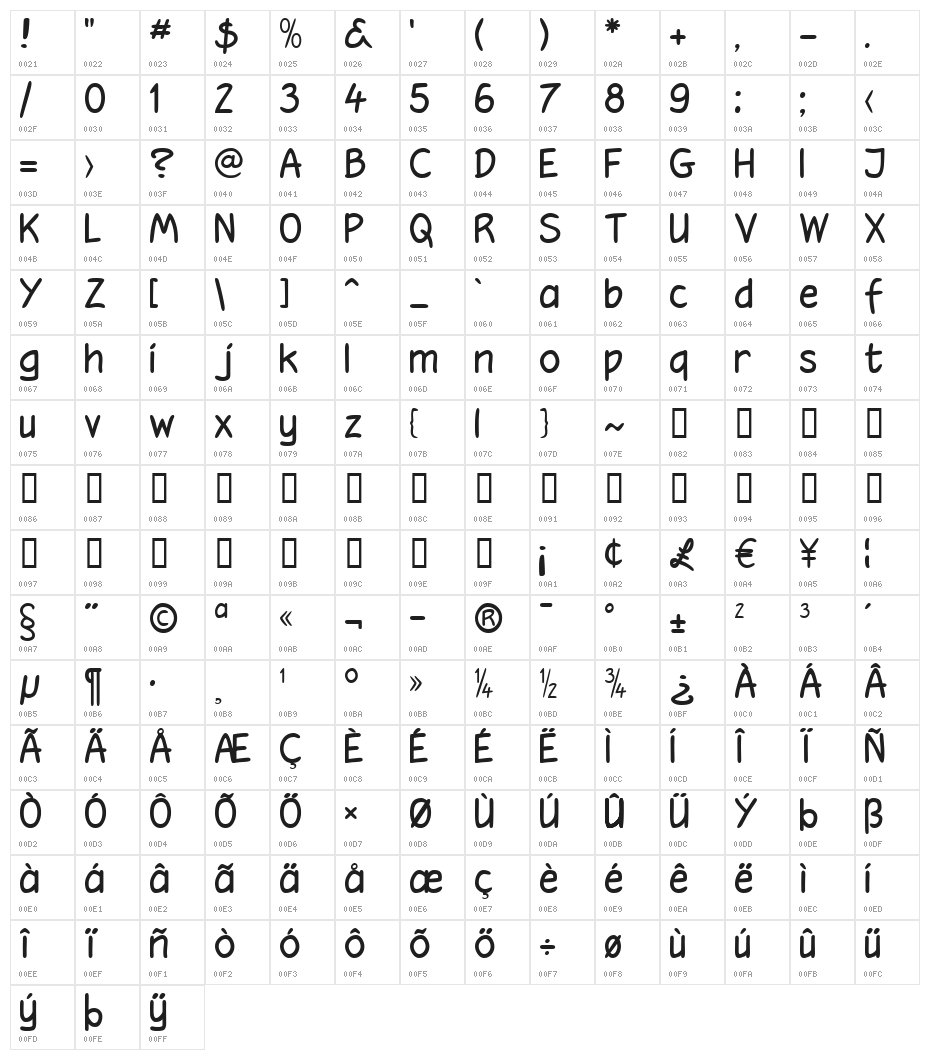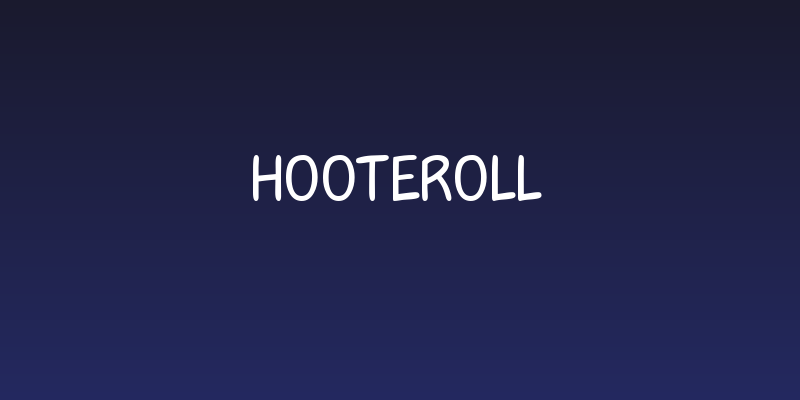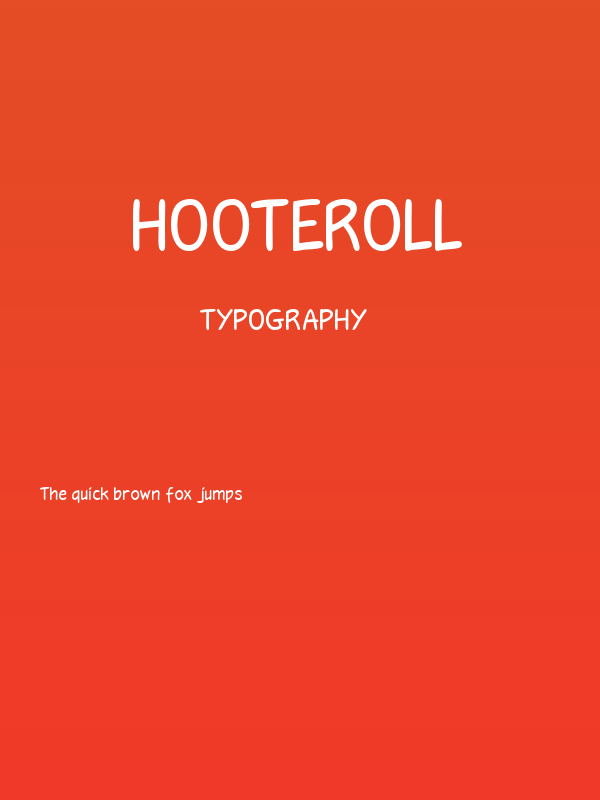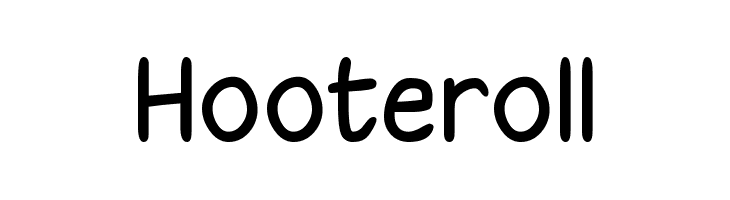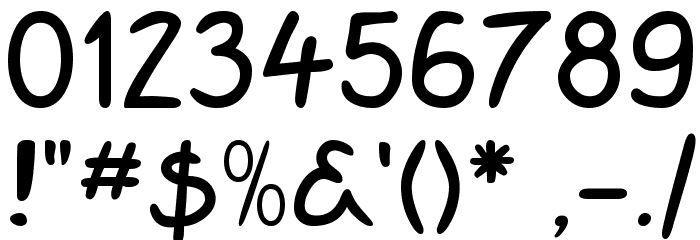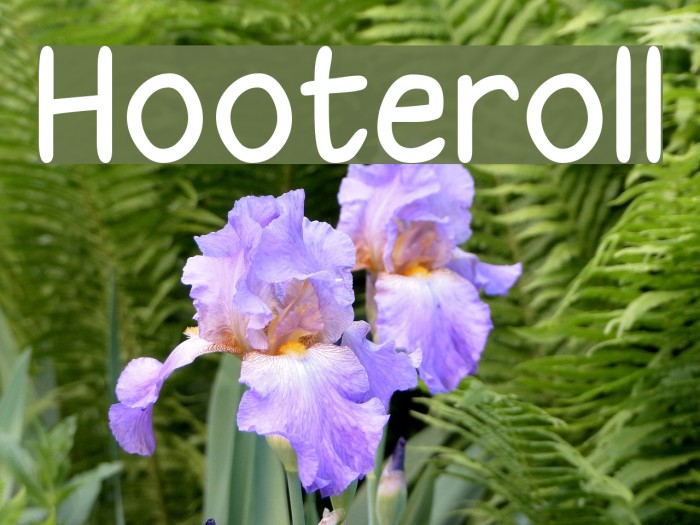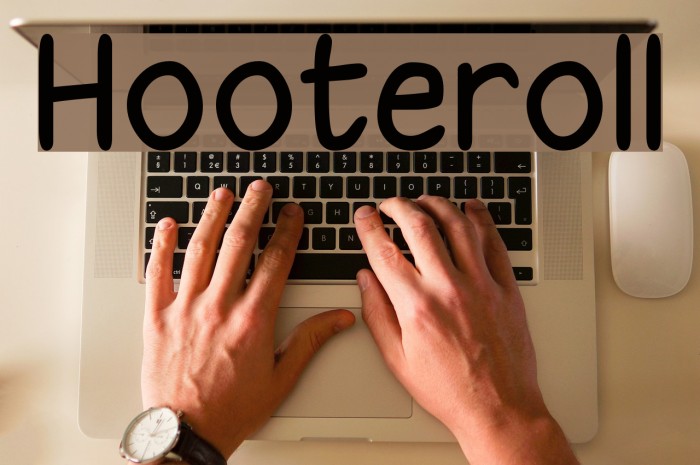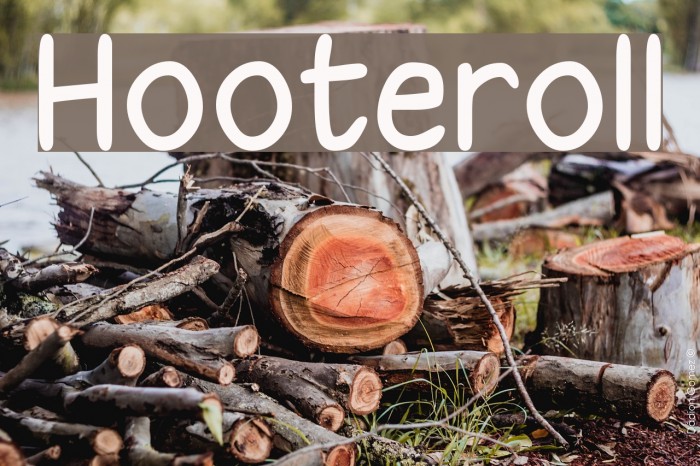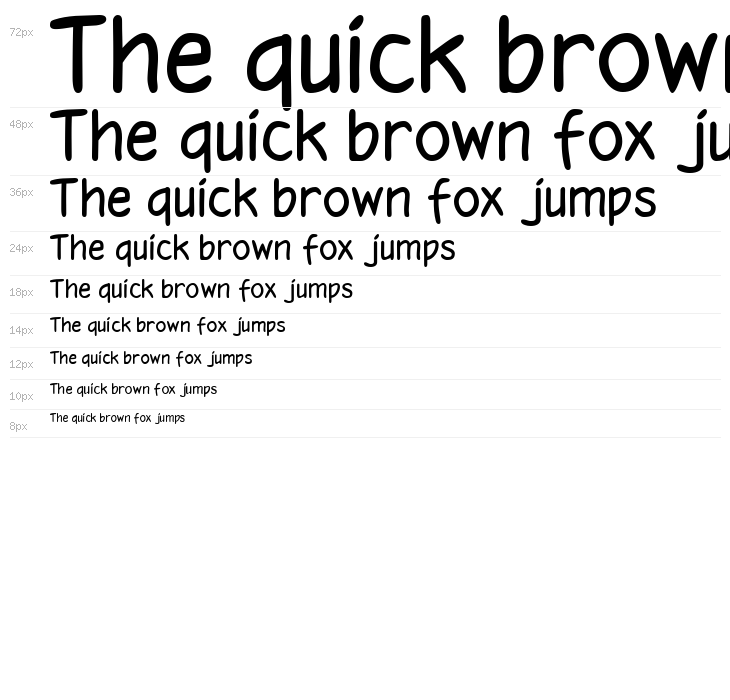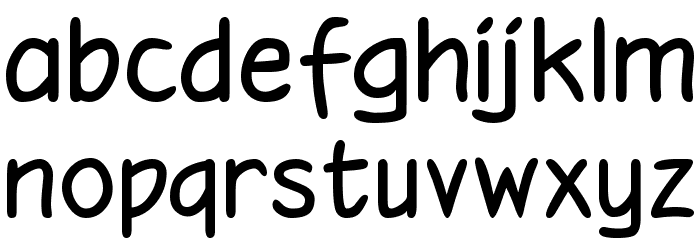
Hooteroll Font
| Gesamtstil | Casual |
| Anwendungsfall | Headlines, Logos, Informal Text |
| Vorgeschlagene Projekte | Ideal for children's books, playful branding, casual invitations, and friendly marketing materials. |